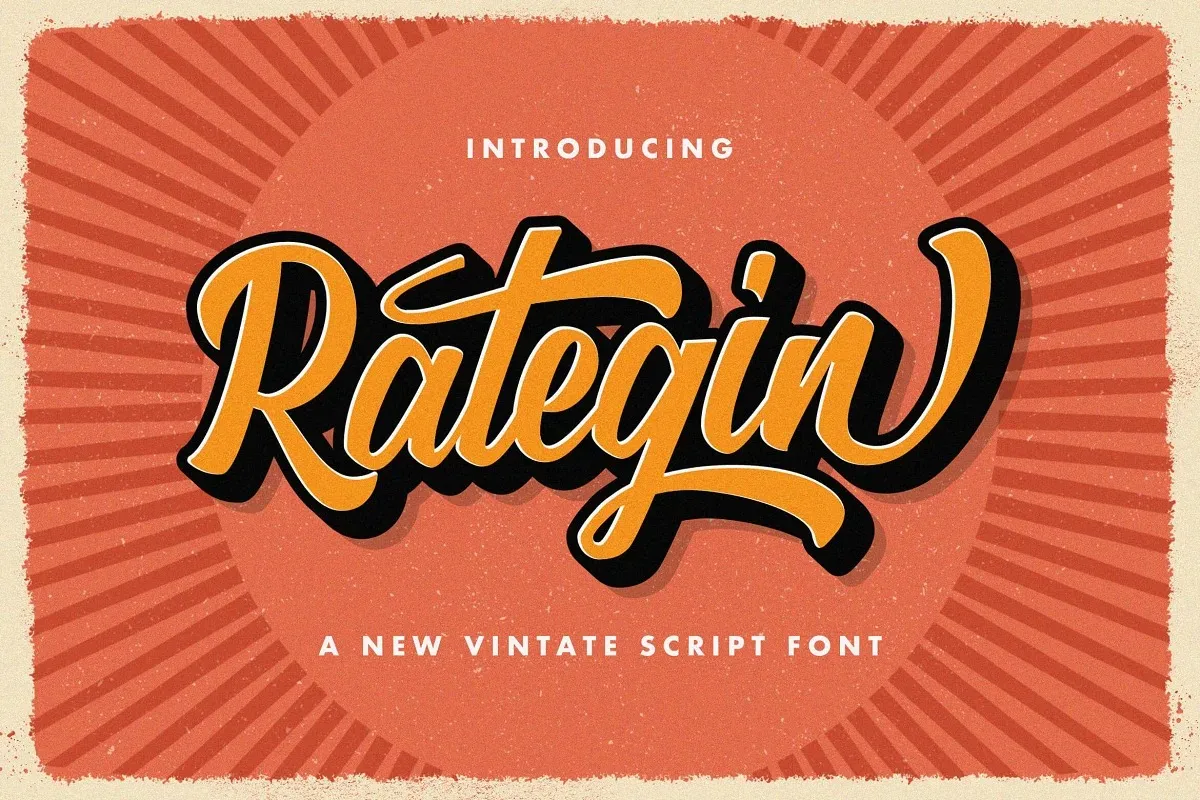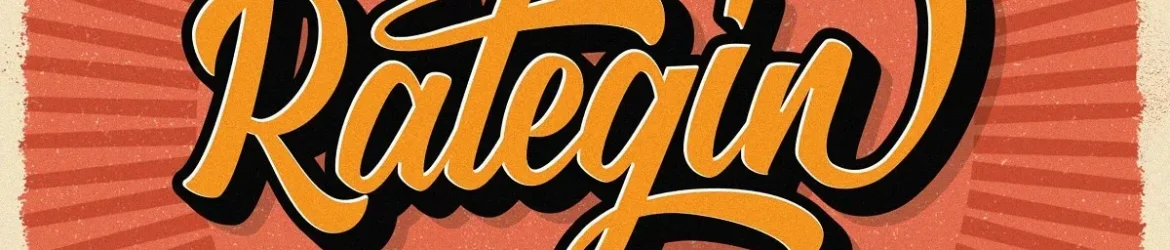
Esta fonte ‘Rategin Font’ tem uma sensação nostálgica devido ao seu estilo, tornando-a perfeitamente adequada para projetos com tema retro/vintage. Seus traços arredondados e suaves criam um charme único que permite criar letras vintage rapidamente. A fonte é ideal tanto para logotipos quanto para diversos usos formais como convites, rótulos, marcas de moda, maquiagem, papelaria, revistas ou qualquer tipo de propósito publicitário. Com sua facilidade em ser adaptada a várias formas formativas, você pode usar essa fonte para criar designs elegantes e distintivos, seculando os estilos mais modernos com uma sensação vintage única. Não importa o projeto que esteja desenvolvendo, ‘Rategin Font’ certamente será um recurso valioso.